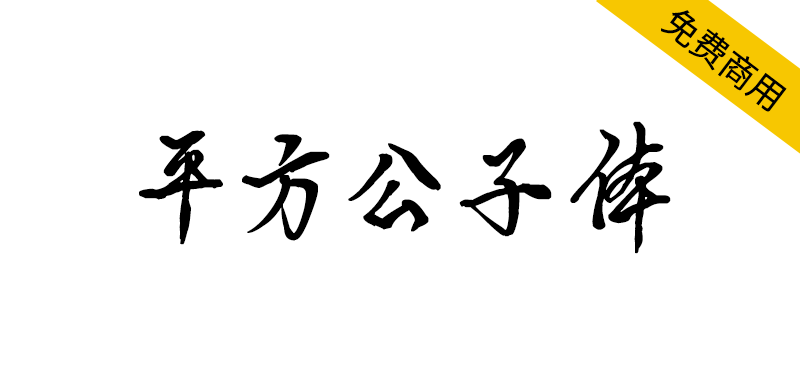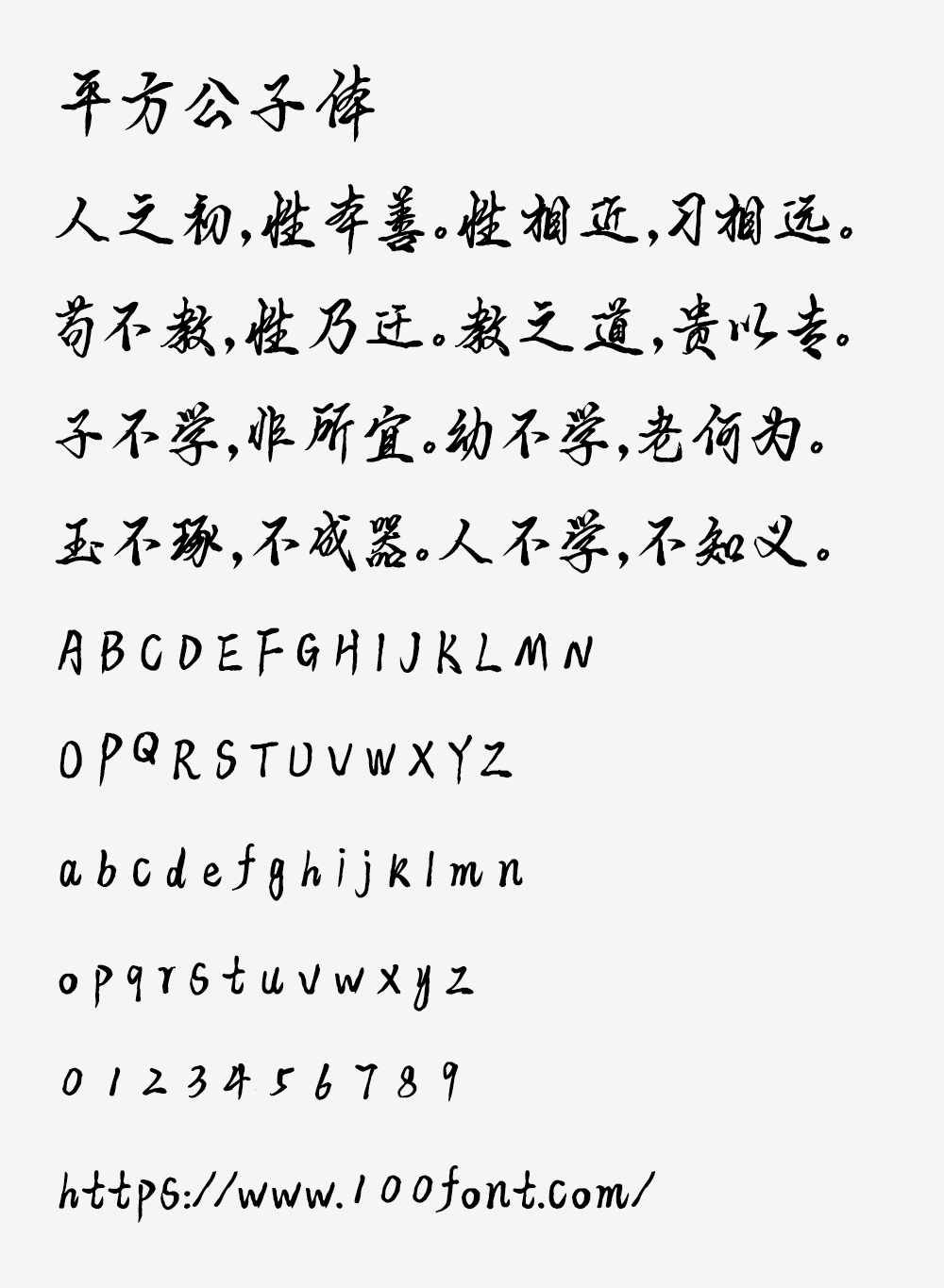
【平方公子体】一款兼具艺术美感与实用性的手写字体
还在为找不到既优雅又免费的商用字体而焦虑?揭秘平方公子体——这款手写字体以严谨端庄的字形、工整利落的笔触,瞬间打破“艺术与实用不可兼得”的魔咒!它简约不失雅致,带来清新隽永的视觉盛宴,更重磅的是:个人和企业均可免费用于广告、自媒体等商业场景,彻底告别字体收费痛点。但注意:不可修改或用于商标。立即在线预览,用免费美学引爆你的设计灵感!
【平方公子体】一款兼具艺术美感与实用性的手写字体
平方公子体是一款兼具艺术美感与实用性的手写字体,其字形严谨端庄,笔触工整利落,风格简约而不失雅致。独特的书写韵味,呈现清新隽永的视觉体验。
【平方公子体】一款兼具艺术美感与实用性的手写字体